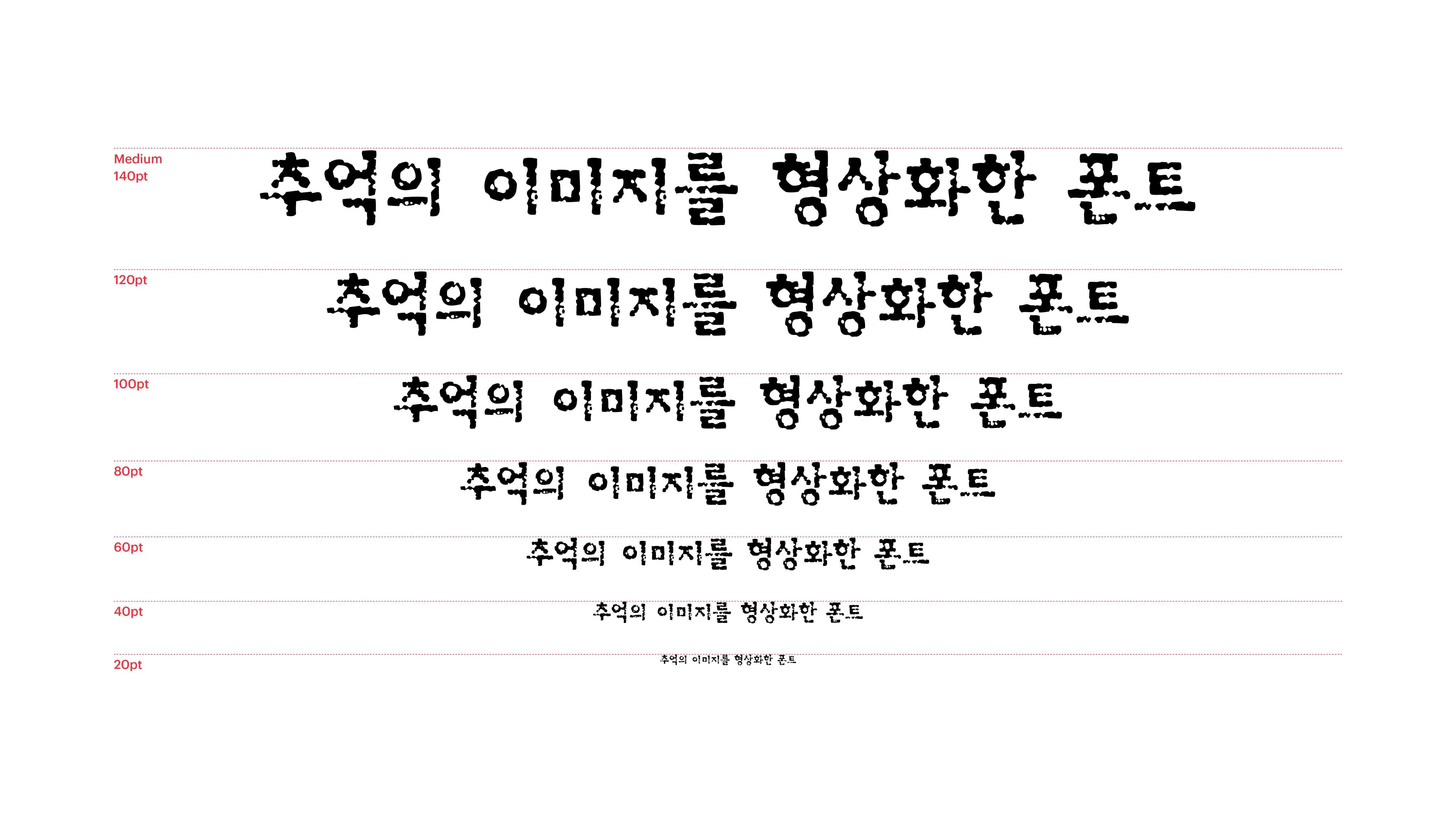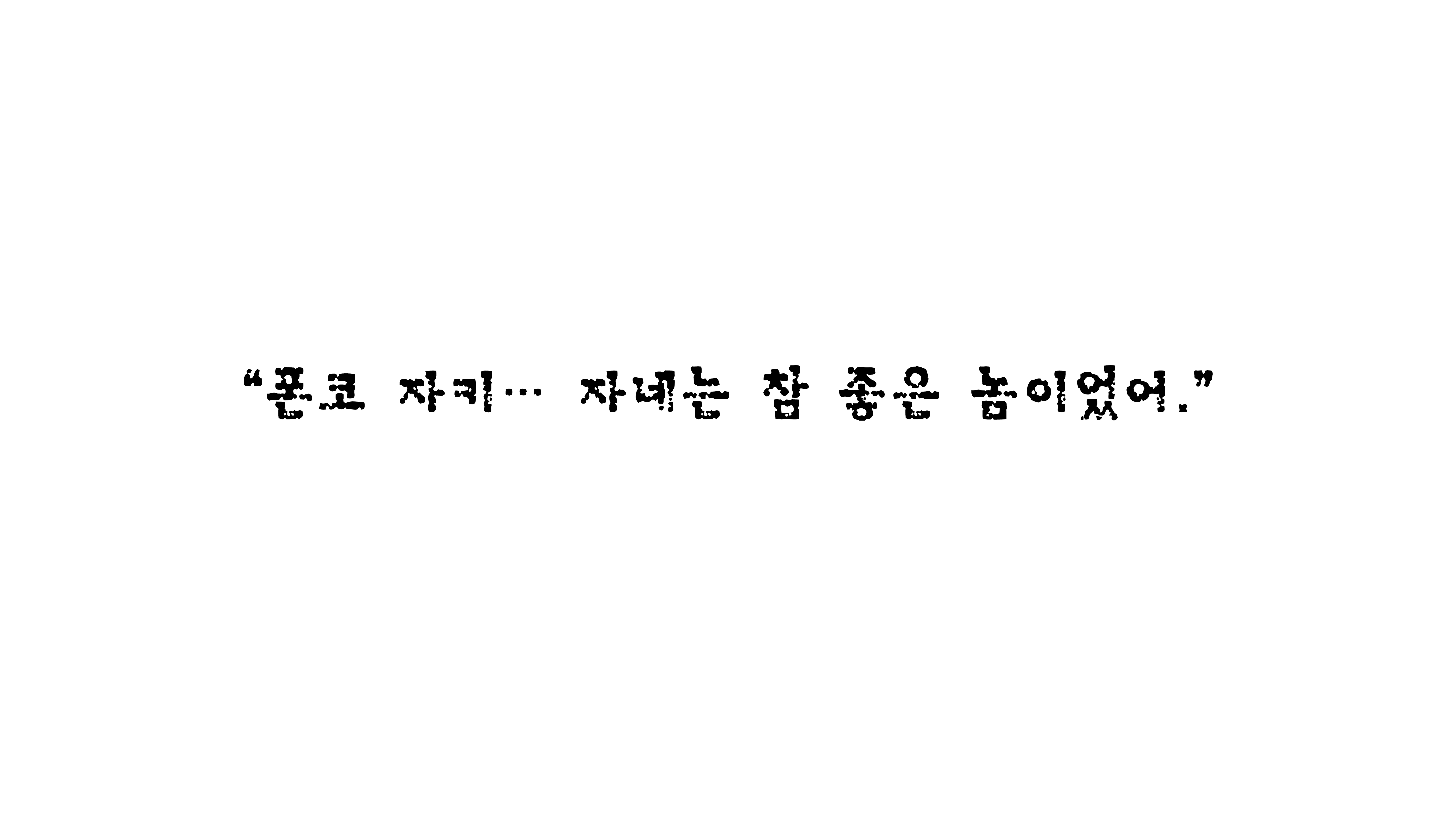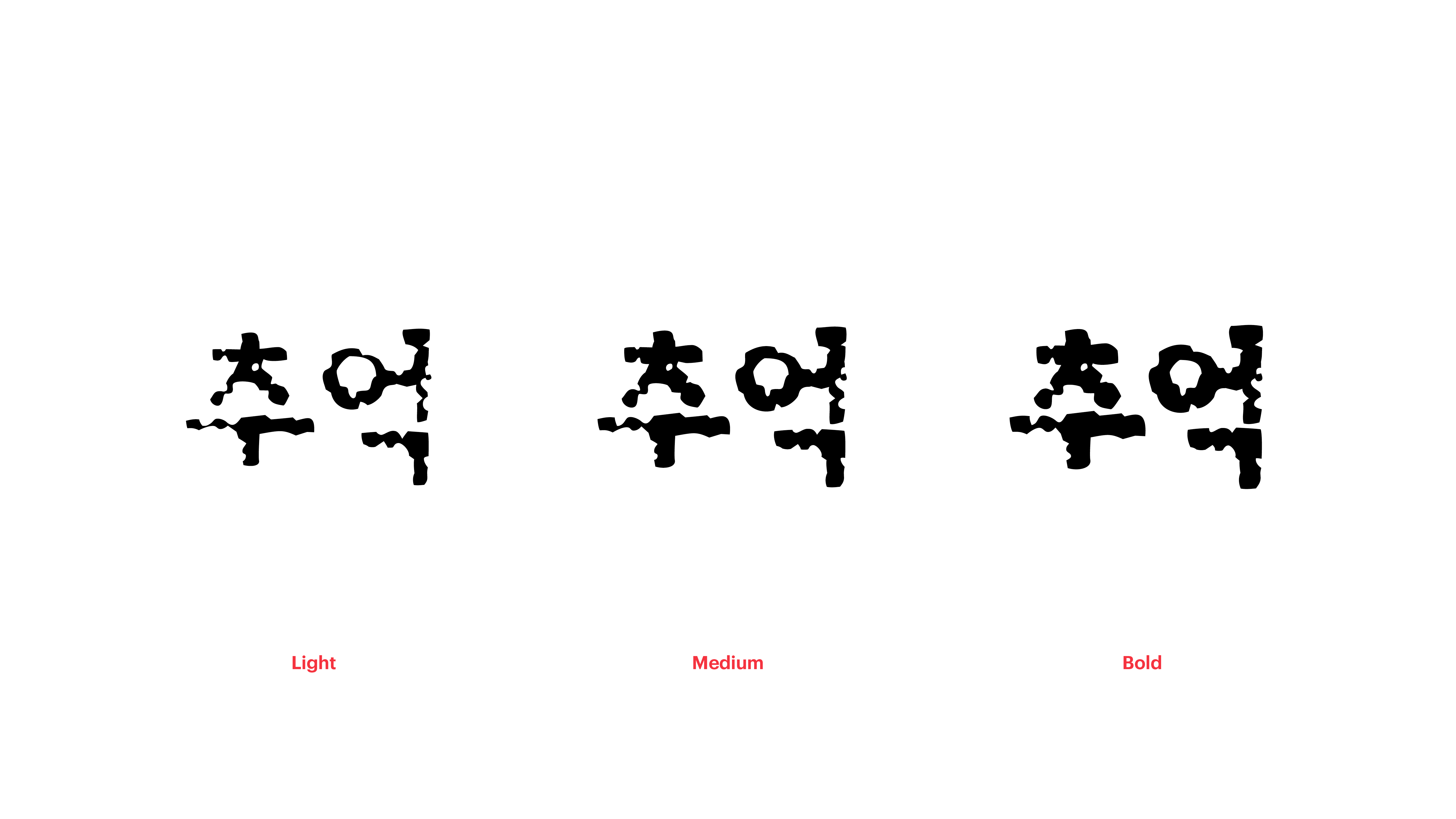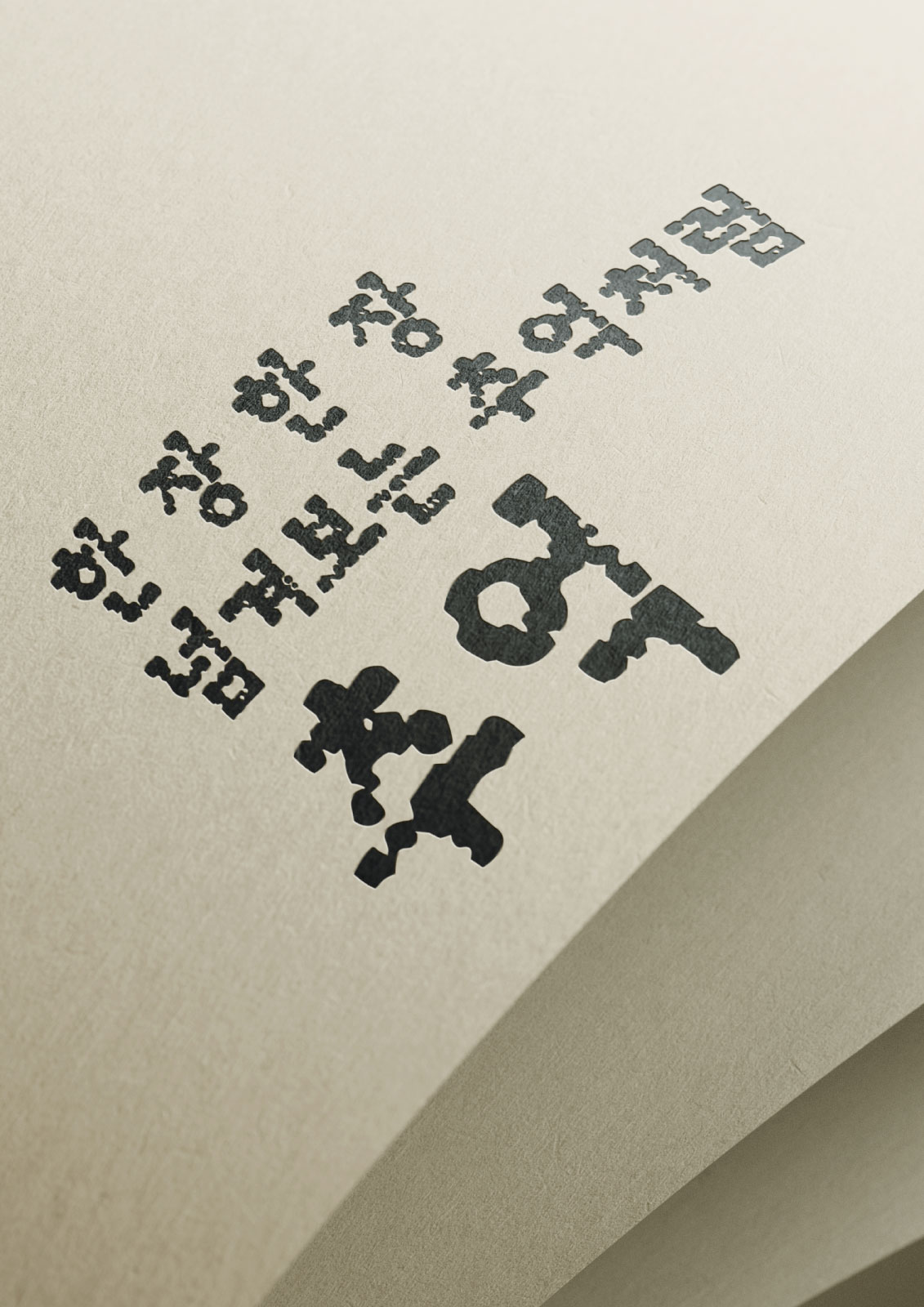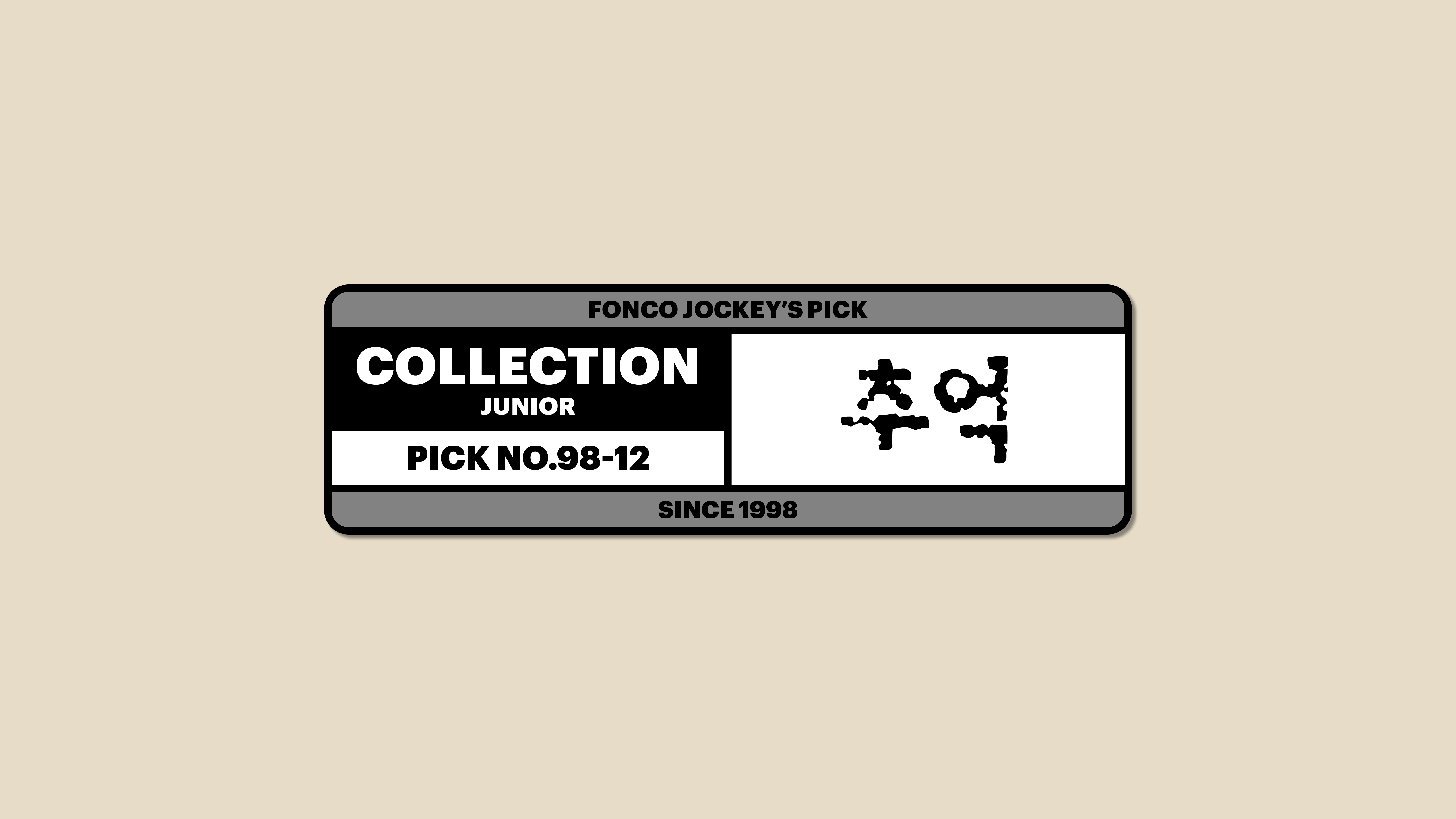
추억
Yoon 추억
오래된 건물을 살피다 보면, 사라진 부분과 보존된 부분이 함께 지어 올린 시간의 건축물 같다는 생각이 듭니다. 추억체도 마찬가지예요. 시간에 의해 부서진 부분은 아련한 질감으로, 여전히 남아 있는 부분은 강인한 직선으로 표현해 소중하게 간직해둔 추억의 이미지를 형상화한 폰트랍니다.